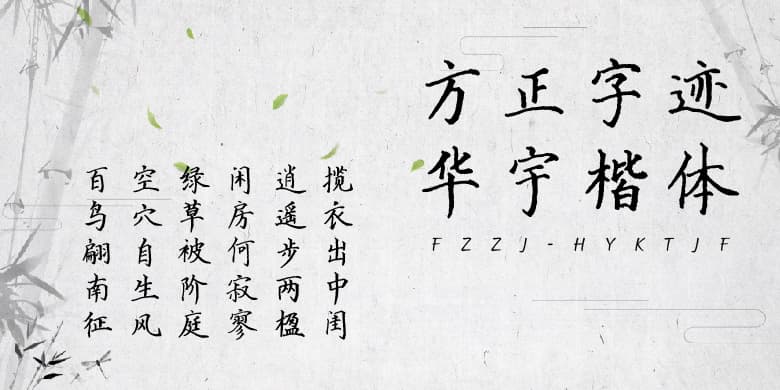
字体介绍 品牌:方正字迹设计师:段云方发行时间:2021字库编码:大陆简体(GB2312-80)、简繁扩展(GBK)分类:常规书写·毛笔字体属性:精品字 英文名称:FZZJ-HYKTJW.TTF、FZZJ-HYKTJF.TTF 方正字迹-华宇楷体,由青年书法家段云方先生创作,这款字体刚健挺拔、体势秀逸、笔致洒脱、结体宽敞舒展,线条遒劲有力。字体适用于文化类宣传设计、商业宣传、日常办公、手机字体使用等。 字体下载 官方下载